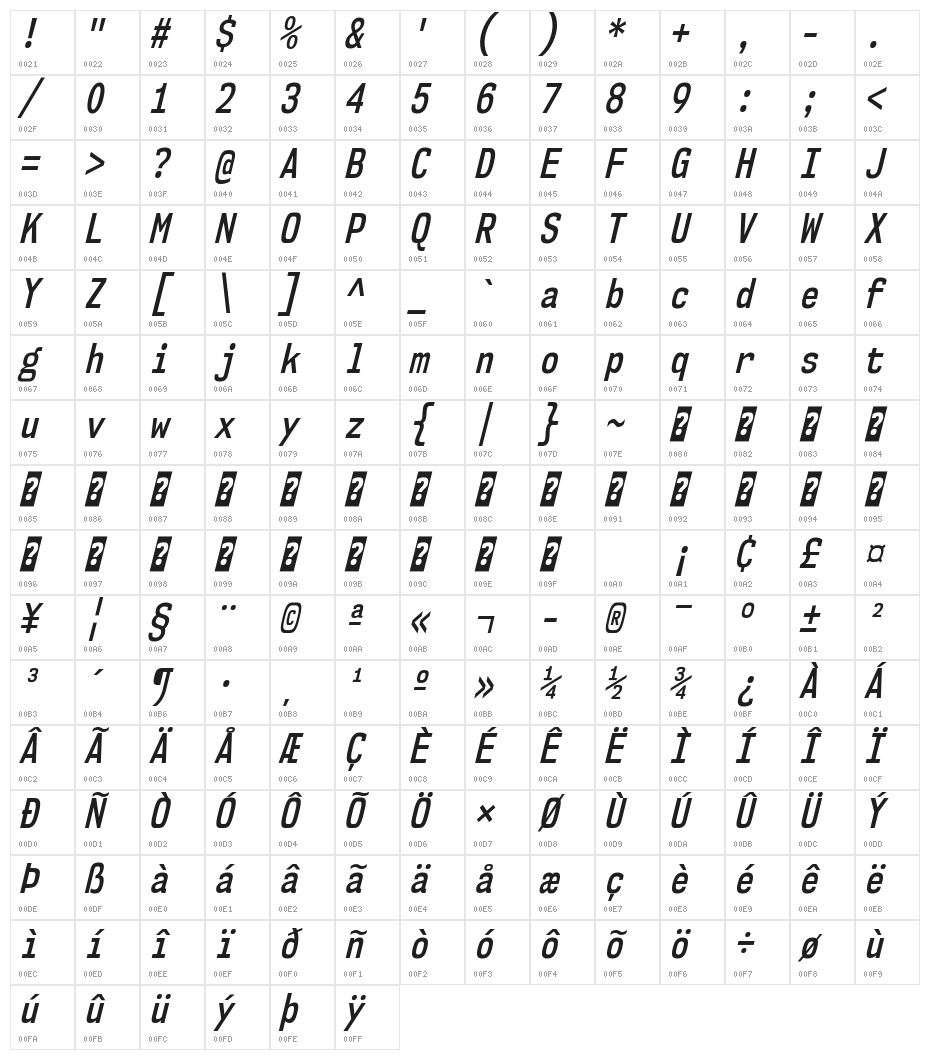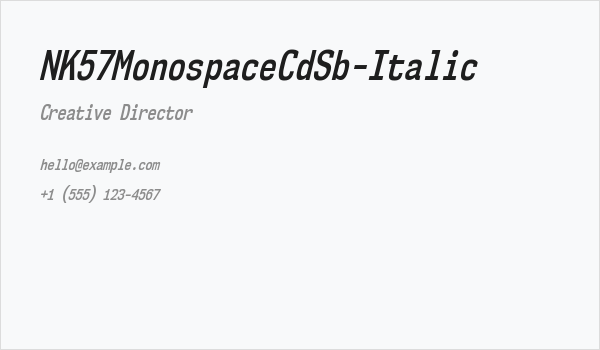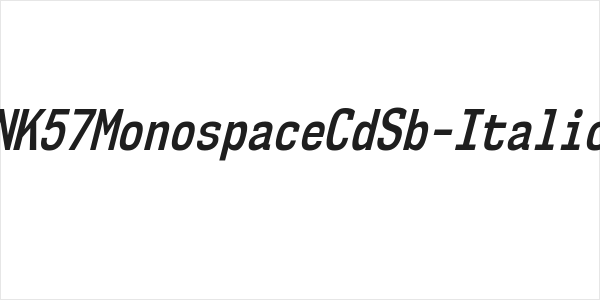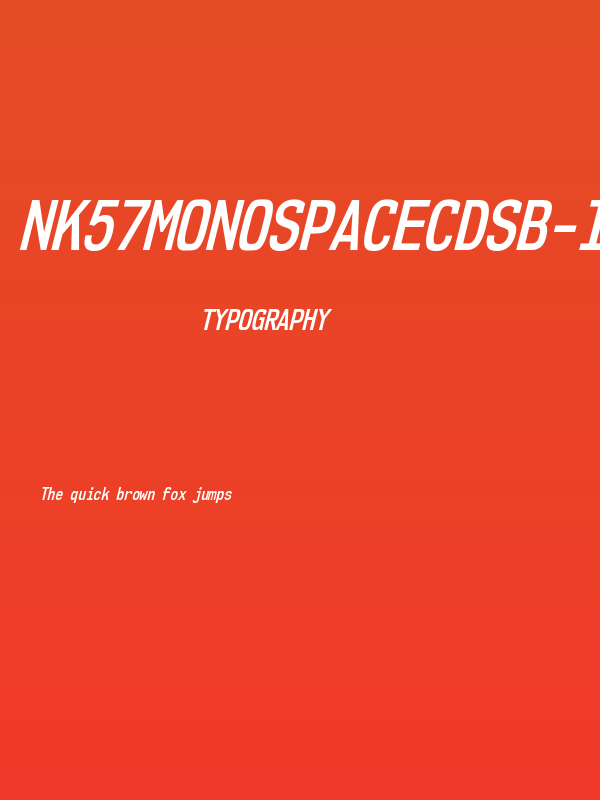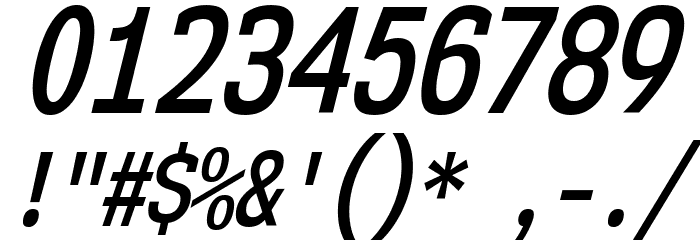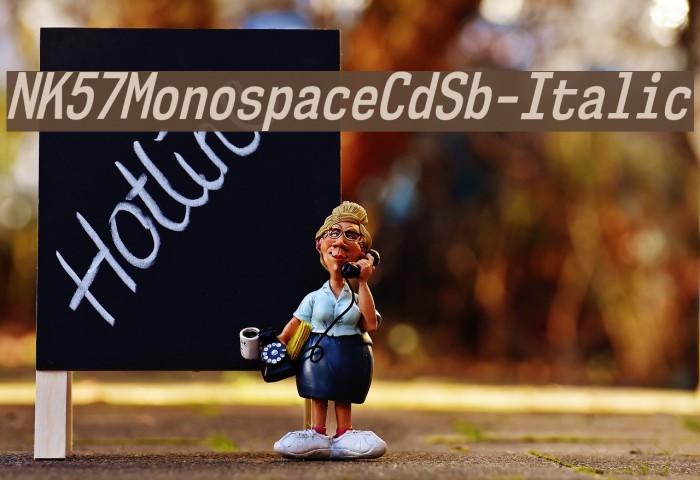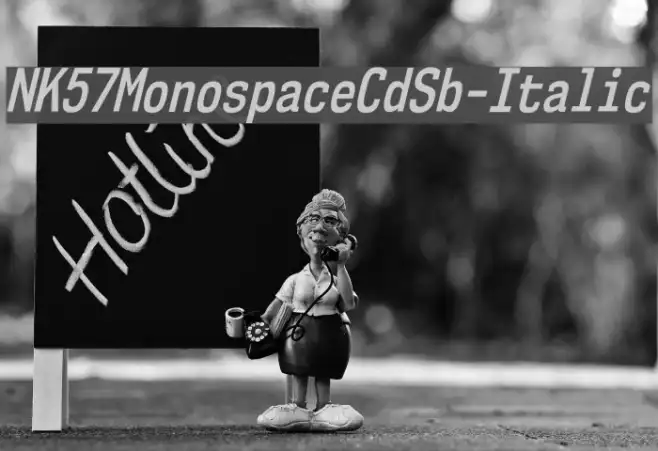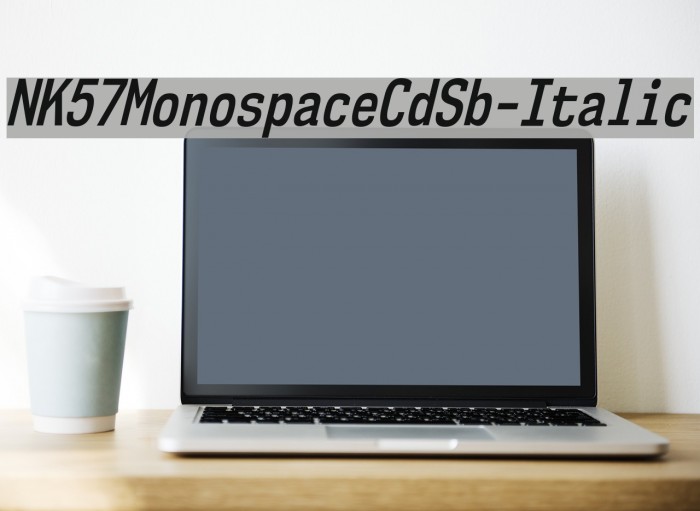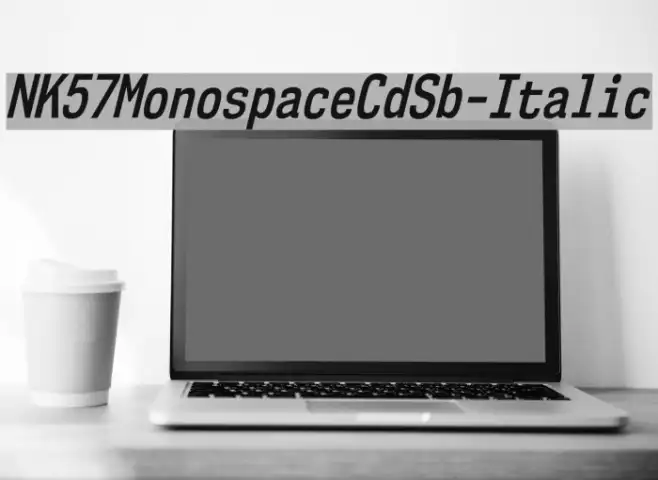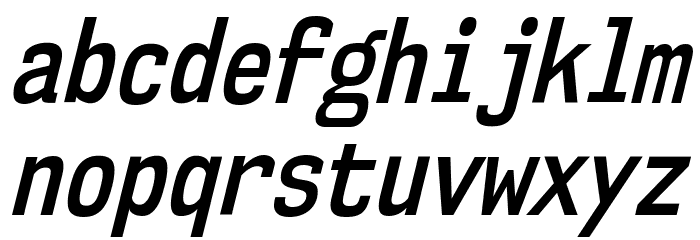
NK57MonospaceCdSb-Italic Font
| Cas d'utilisation | Coding, Technical documentation, Digital interfaces |
| Projets proposés | Ideal for coding, technical documentation, and digital interfaces where readability and space efficiency are crucial. |